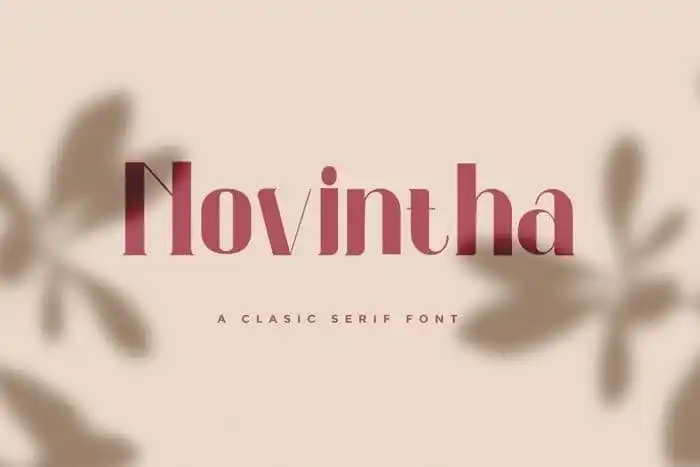
Novintha Serif Font – Download Grátis
Novintha Serif é uma elegante tipografia serif que surgiu no ateliê da Rantautype na 99designs. Inspirada nos espaçados tipos de fontes, Novintha é perfeitamente adaptável a aplicativos como logotipos, sinais e revistas fashion. Suas linhas definidas e robustas lhe conferem um estilo sólido e autêntico que faz qualquer projeto ganhar mais poder visual. Ideal tanto para projetos web quanto para sinalização, corporativos ou design editorial, a Novintha Serif é uma escolha certeira para qualquer iniciativa que valoriza elegância e força no seu desenho. Experimente incorporar sua tipografia moderna em projetos futuros e revitalize o estilo de suas criações.